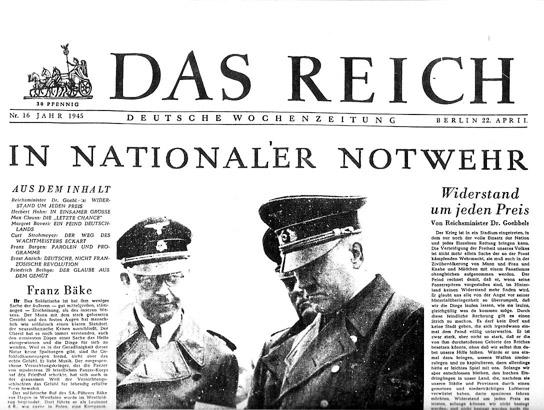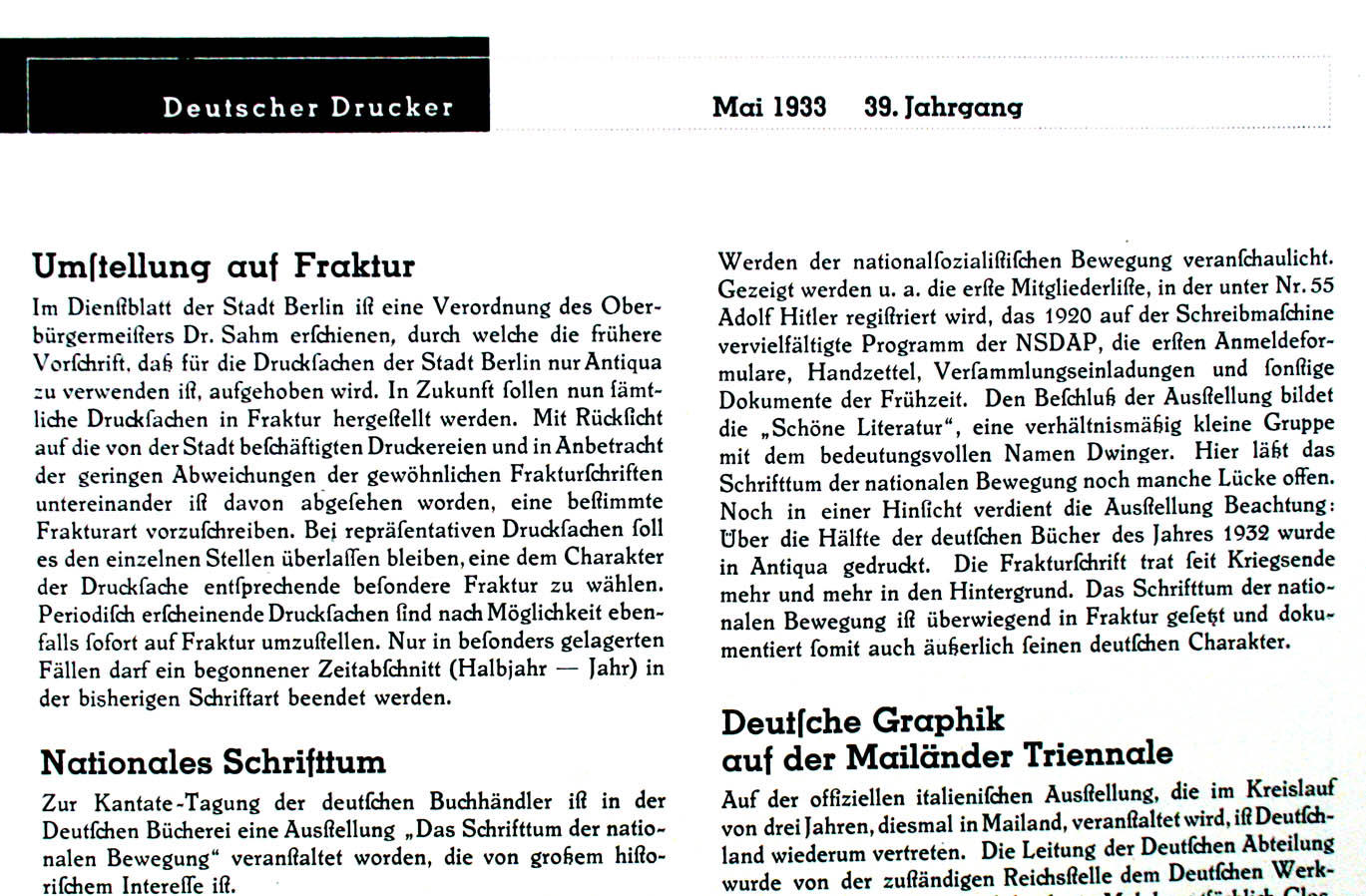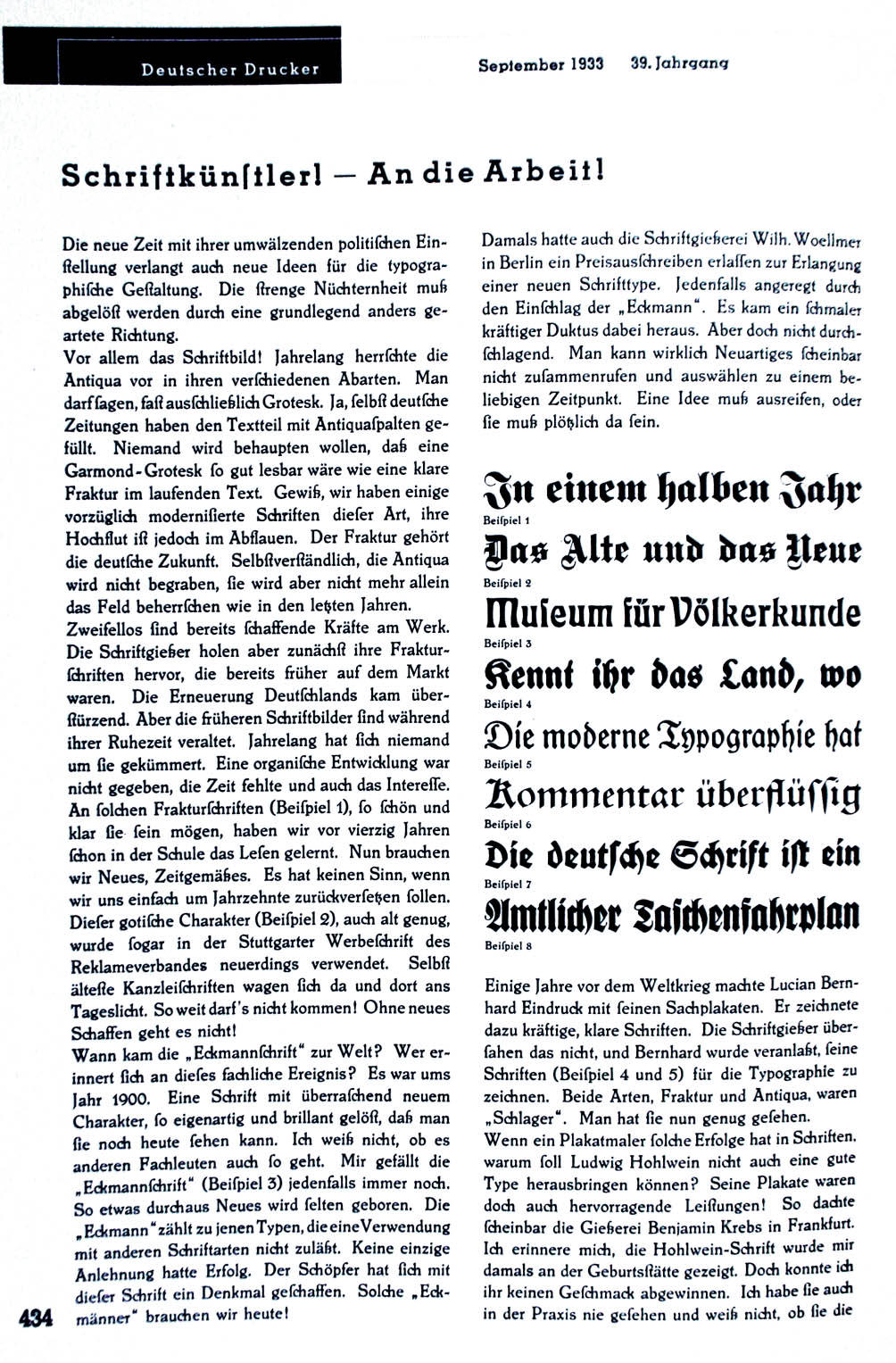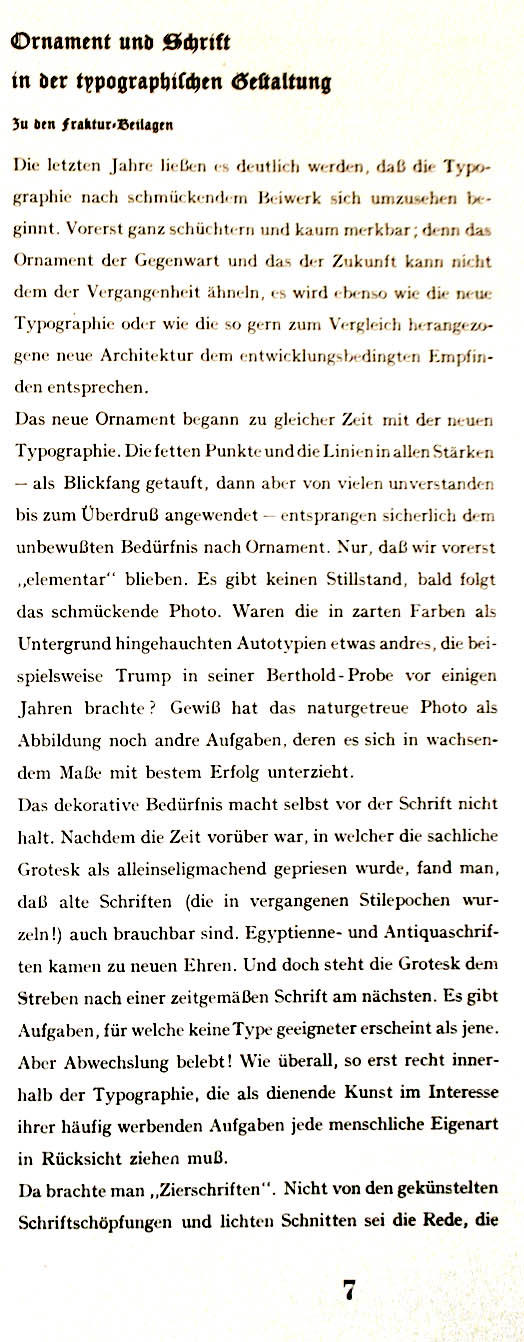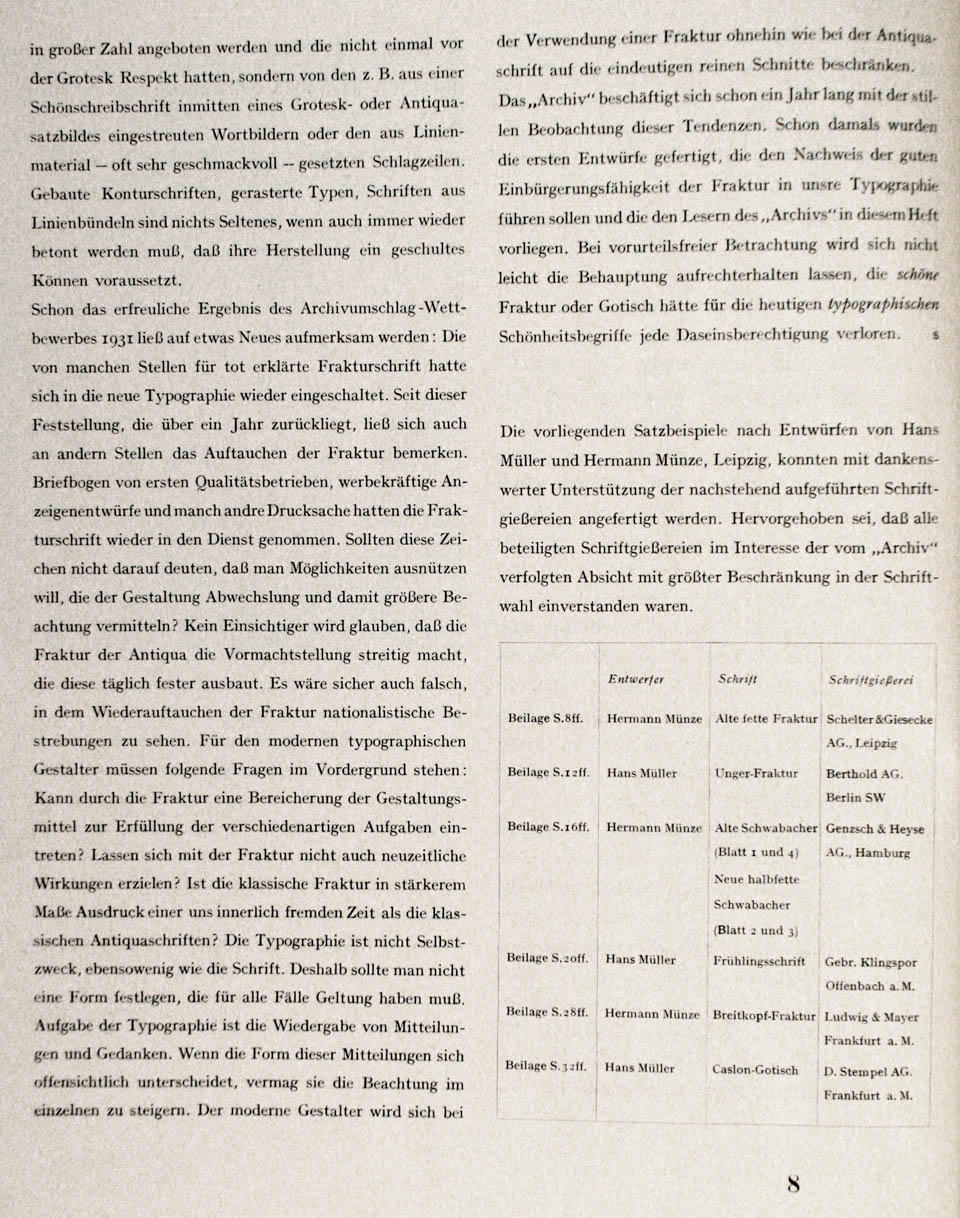
Welche Schriften im Dritten Reich und in der DDR?
Welche Schriften benützte das Dritte Reich? Welche lehnte es ab?
Welche Schriften benützte die DDR? Welche lehnte sie ab?
Waren Frakturschriften anfangs typisch den Nationalsozialismus? Wurden sie später tatsächlich verboten?
Welche Schriften benützte das Dritte Reich? Welche lehnte es ab?
Welche Schriften benützte die DDR? Welche lehnte sie ab?
Das kann man so absolut nicht sagen, denn Schriften werden ja nicht von einem abstrakten Reich oder einem Staat benutzt, sondern von Individuen.
Im Dritten Reich wurde erst mal weiterbenutzt, was aus der Weimarer Republik in den Setzkästen lag. In der DDR war die Schriftenauswahl im wesentlichen auf das Typoart-Programm beschränkt. Im Vergleich zu heutigen Sehgewohnheiten war das eine extrem schmale Auswahl, so daß einem immer wieder die gleichen Schriften begegneten. Hier muß unbedingt die »Super« Erwähnung finden, die das Gesicht der »gedruckten DDR« weit mehr geprägt hat als jede andere Schrift und auch weit mehr »Marktanteil« hatte als z. B. heute die Helvetica. Frakturschriften galten als »rückwärtsgewandt« und wurden in offiziellen Texten nicht verwendet.
Waren Frakturschriften anfangs typisch den Nationalsozialismus? Wurden sie später tatsächlich verboten?
Im Nationalsozialismus gab es zunächst die gegensätzlichen Denkansätze, die die Frakturdiskussion schon in der Weimarer Republik geprägt hatten. Durchgesetzt hat sich letztlich Hitler mit seinem Verdikt gegen die Fraktur: http://www.e-welt.net/bfds_2003/bund/sc ... hichte.htm Die Bezeichnung der Fraktur als »Schwabacher Judenlettern« war natürlich unsinnig, eigentlich ging es wohl darum, daß man meinte, daß der deutsche typographische Sonderweg Fraktur hinderlich sei bei der Installation eines europäischen Großreiches. So wurde die deutsche Schrift aus Amtsstuben und Schulen verbannt (ansonsten war ihr privater Gebrauch nicht verboten, aber »politisch unkorrekt«), und bis heute ist sie nicht in die Schulen zurückgekehrt.
Wenn heute mitunter Frakturschriften als »Nazischriften« diskreditiert werden, ist das genauso unwissenschaftlich wie die nationalsozialistische Bezeichnung als »Schwabacher Judenlettern«.
Man kann darüber streiten, ob die Entstehung von Schriften wie der »Tannenberg« ideologisch beeinflußt war. Ganz allgemein gehen diese Schriften, die auch als »Schaftstiefelgrotesk« bezeichnet wurden, auf das Bestreben zurück, der Fraktur ein modernes, zeitgemäßes Gewand zu verpassen. Da steckt viel Bauhausdenken drin, auch wenn das sicher kein Bauhäusler hören will. Die Verbindung der Attribute »deutsch« und »modern« hat diesen Schriften dann zu einiger Verbreitung im frühen Nationalsozialismus verholfen, der sich ja mit ebendiesen Attributen geschmückt hat; sie deshalb als nationalsozialistisch zu bezeichnen, greift aber deutlich zu kurz. Der Gedanke, eine Fraktur mit einer Grotesk zu kreuzen, war auch so zeitgeistgemäß und hätte des Nationalsozialismus nicht bedurft.
man muss aber ergänzen, dass heute viele typografie-laien fraktur zuerst mit dem ›dritten reich‹ assoziieren. was die benutzung solcher schriften im jahr 2008 angeht, halte ich diesen punkt für mindestens so wichtig wie historische betrachtungen, auch wenn die zutreffend sind. die geschichtliche wahrheit wird da nicht über die empfindung der massen siegen.
Daß deutsche Geschichte sich in der »Empfindung der Massen« oft auf 12 Jahre reduziert, ist ja ein Problem, das über die Typographie hinausreicht. Ich denke nicht, daß man sich deswegen von der Fraktur distanzieren sollte.
für die fraktur gilt imho dasselbe wie für manche wörter, die angeblich nazi-vokabular waren: man kann sie verwenden, aber man sollte sich überlegen, in welchem zusammenhang. vor einem verständigen publikum, dem ich ggf. die zusammenhänge erklären kann, ist das möglich. habe ich nicht die chance, meine wahl zu erläutern, verzichte ich lieber darauf, weil gewisse assoziationen einfach da sind und ich eventuell missverstanden werde. mir geht es also weniger um das distanzieren als um das bewusstsein für geschichte und heutige wirkung.
Das ist im Prinzip richtig, schließlich konnte Hindenburg nicht per 30. Januar 1933 neue Schriften in die Setzkästen hinein dekretieren. Allerdings kann man nicht sagen, dass ab dem 31. Januar 33 völlige Orientierungslosigkeit herrschte, welche Schriften der heraufziehende Führerstaat wohl gerne sähe. Im Gegenteil: wer zeitgenössische Quellen untersucht, wird feststellen, dass die Industrie sich atemberaubend schnell und opportunistisch auf den neuen Wind eingestellt hatte. Falls ich in den kommenden Tagen Lust und Zeit habe, stelle ich vielleicht das eine oder andere Beweisstück dazu ein. 1934 beispielsweise gab es in der Fachpresse bereits praktisch keine Werbung mehr für andere als gebrochene Schriften (die Sammelbezeichnung Fraktur für alle gebrochenen Schriften war schon damals notorisch). Noch zwei Jahre zuvor umfasste der vorherrschende Trend in der Typografiewerbung hingegen Handschriften, geometrische Serifenlose (Futura et al) und serifenbetonte Antiquas (City, Memphis und Co.), jedoch praktisch keine gebrochenen. Bevor jemand einen Roman von Adalbert Stifter oder Fritz Reuter als «Gegenbeweis» aus der Tasche zieht: Ich rede von Werbeanzeigen der Schriftgiessereien.
An dieser Stelle möchte ich doch empfehlen, etwas von Willberg, Hartmann und Kapr zu diesem Thema lesen, um den in der Tat schon deutlich vor 1933 existierenden Fraktur-Antiqua-Streit überhaupt zu verstehen. Zur Not und auf die Schnelle tut's natürlich auch der Wikipedia-Eintrag: http://de.wikipedia.org/wiki/Antiqua-Fraktur-Streit. Keine Unsicherheit kann allerdings darüber bestehen, dass in der Fachwelt 1933 ganz offenbar völlige Einigkeit darüber bestand, dass ebendieser Fraktur-Antiqua-Streit mit der Regierungsübernahme der NSDAP zugleich zugunsten der Fraktur entschieden war. Hierzu werde ich ganz sicher morgen das eine oder andere Beweisstück heraussuchen, das wollte ich schon immer tun.
P.S. Wer hat den Schriften damals eigentlich üblicherweise den Namen gegeben? Die Gießerei oder Schriftgestalter?
wird das Design eines Stuhls automatisch politisch, nur weil ein Nazi darauf gesessen hat?